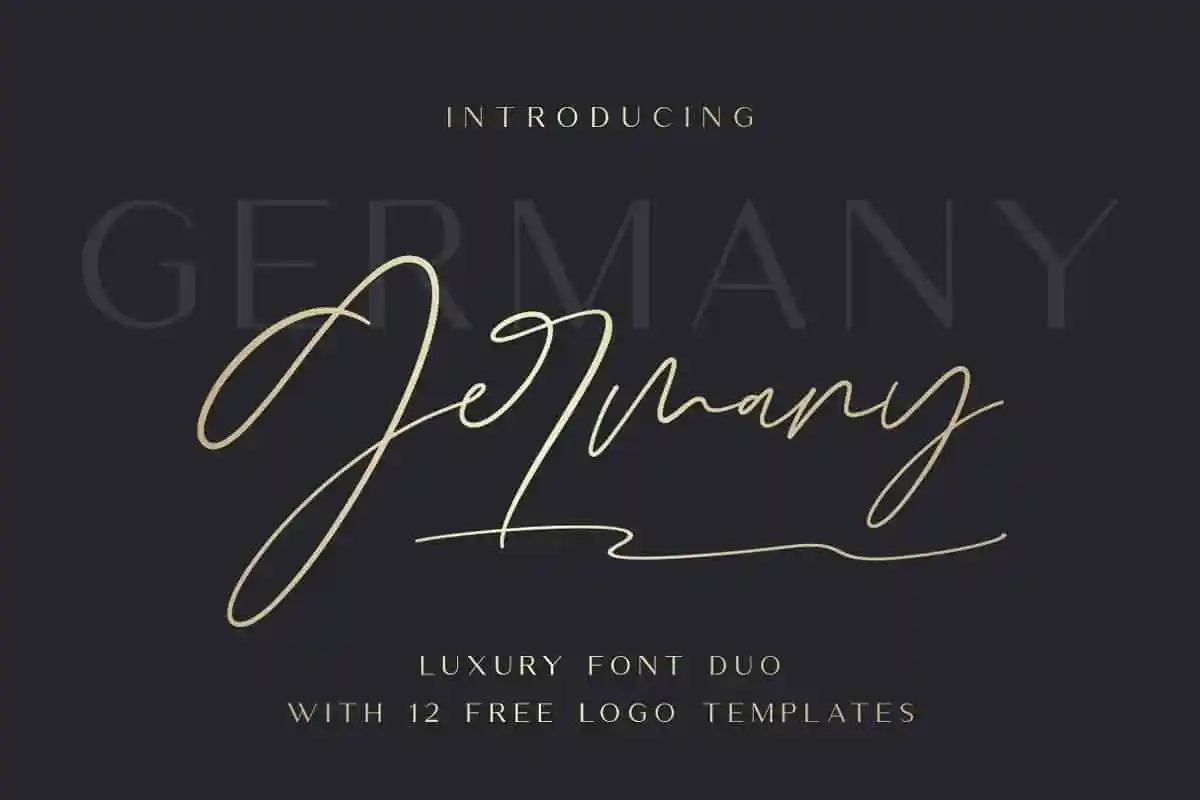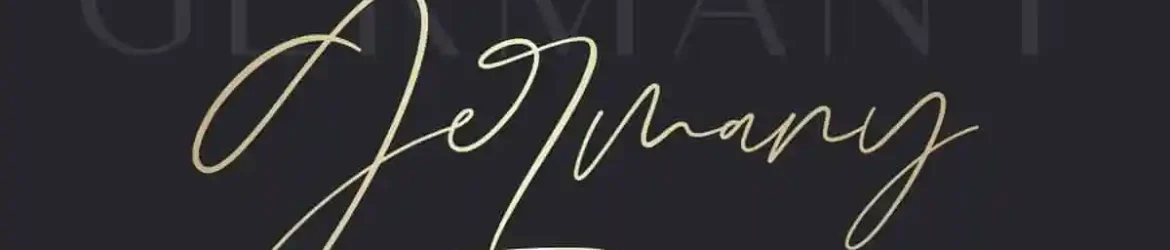
Germany Font Duo – Download Grátis
Esta é uma fonte feita à mão que oferece uma assinatura única. Ideal para quem deseja expressar sofisticação e modernidade. Esta font está certamente destinada a atrair compradores contemporâneos. Introduzimos o Duo de Fontes Luxuosas Alemãs. Compreendendo harmonia tipográfica refinada, esta font é ideal para uma variedade de projetos de design, incluindo logomarcas e identidades corporativas, designs de casamentos, postagens nas redes sociais, anúncios e designs de produtos. Acredito que você vai adorar o seu jeito clean e elegante. Em breve você poderá desfrutar deste Duo.